๊ตฌ๋ฆ์์ ํ์ด๋ ํจ๋ฐ๋ฆฌ
์์นจ์ ๊ฐ์ฅ ๋จผ์ ํ์ธํ๋ ์ค๋งํธํฐ, ์น๊ตฌ๋ค๊ณผ ๋ํ๋ฅผ ๋๋๋ ๋ฉ์ ์ , ์ถ๊ทผ๊ธธ ์งํ์ฒ ์ ์๋ด ์ฌ์ธ, ์ฐ๋ฆฌ ๋๋ค ์๊ฐ์ ๊ฐํ, ์์ฃผ ๊ฐ๋ ์๋น์ ๋ฉ๋ดํ ๋ฑ. ์ฐ๋ฆฌ๋ ์์ฐ์ค๋ฝ๊ฒ ํฐํธ์ ๋ง์ฃผํ๋ฉฐ ์ด์๊ฐ๋๋ฐ์. ๋๋ถ๋ถ์ ์ฌ๋๋ค์ ์ด๋ฅผ ์ธ์งํ์ง ๋ชปํฉ๋๋ค. ์ด๋ ๋ฏ ํฐํธ๋ ์ฐ๋ฆฌ์๊ฒ ์น์ํ๊ณ ๋ ๋ฏ์ ์กด์ฌ์ธ๋ฐ์. ์ค๋์ ๋๊ตฐ๊ฐ์๊ฒ๋ ๋ฏ์ค ์ ์๋ ํฐํธ์ ๊ฐ๋
์ ์ฐ๋๊ตฌ๋ฆ์ด ํ์ด๋ด๋ ๋ฐฉ์์ ๋ํด ์ด์ผ๊ธฐํ๊ณ ์ ํฉ๋๋ค.
์ผ์์์ ์ ํ๋ ๋ค์ํ ํฐํธ
ํฐํธ ํ์ ์บ๋ฆญํฐ
์ฐ๋๊ตฌ๋ฆ์ ๋ค์ํ ํฐํธ๋ฅผ ๋ณด์ ํ ํ๋ซํผ์ผ๋ก์ ๋ณต์กํ ํฐํธ์ ๊ฐ๋
์ ์ฝ๊ฒ ์ ๋ฌํ ์ ์๋ ๋ฐฉ๋ฒ์ ํญ์ ๊ณ ๋ฏผํ๊ณ ์์ต๋๋ค. ์ด๋ฐ ๋ฐฉ๋ฒ ์ค ํ๋๋ก ‘์บ๋ฆญํฐ๋ฅผ ํตํ ์ปค๋ฎค๋์ผ์ด์
’์ด๋ผ๋ ์์ด๋์ด๊ฐ ์์๋๋ฐ์. ๋ฑ๋ฑํ ์ ์๋ ๊ธ์ค์ ์ค๋ช
๋์ ์บ๋ฆญํฐ๋ฅผ ํตํด ๋ค์ ๋ฏ์ ํฐํธ์ ๊ฐ๋
์ ์น๊ทผํ๊ฒ ์ ๋ฌํ ์ ์์ ๊ฒ์ด๋ผ ์๊ฐ๋์์ต๋๋ค. ๊ทธ๋์ ๊ทธ ์์ฒด๋ก ํฐํธ๋ฅผ ์ฐ์์ํฌ ์ ์๋๋ก ํฐํธ์ ์ฑ์ง์ ๋ฐ์ํ ์บ๋ฆญํฐ๋ฅผ ๊ฐ๋ฐํ๊ฒ ๋์์ต๋๋ค.
์ฐ๋๊ตฌ๋ฆ ํจ๋ฐ๋ฆฌ
๊ตฌ๋ฆ์์ ํ์ด๋ ํจ๋ฐ๋ฆฌ
์บ๋ฆญํฐ์ ๋ํ ์ด์ผ๊ธฐ๋ฅผ ํ๊ธฐ ์์ ํฐํธ ํจ๋ฐ๋ฆฌ์ ๊ดํ ์ค๋ช
์ด ํ์ํฉ๋๋ค. ํฐํธ ํจ๋ฐ๋ฆฌ๋ฅผ ์ฝ๊ฒ ๋งํ๋ฉด ํ๋์ ํฐํธ๋ฅผ ๊ธฐ์ค์ผ๋ก ๋ค์ํ ๋ณํ์ด ์๋ ํฐํธ์ ๋ชจ์์ธ๋ฐ์.
ํฐํธ ํจ๋ฐ๋ฆฌ๋ง๋ค ๊ทธ ๊ตฌ์ฑ์ ์กฐ๊ธ์ฉ ๋ค๋ฅด์ง๋ง ์์ ๋๊ป์ ๋ผ์ดํธ Light, ์ค๊ฐ ๋๊ป์ ๋ ๊ทค๋ฌ Regular, ๊ตต์ ๋๊ป์ ๋ณผ๋ Bold, ๊ธฐ์ธ๊ธฐ๊ฐ ์ ์ฉ๋ ์ดํค๋ฆญ Italic ๋ฑ์ผ๋ก ํจ๋ฐ๋ฆฌ๊ฐ ๊ตฌ์ฑ๋ฉ๋๋ค. ํจ๋ฐ๋ฆฌ๋ฅผ ๊ตฌ์ฑํ๋ ํฐํธ๋ค์ ์ ์ฒด๋ฅผ ๊ดํตํ๋ ํฐ ์ปจ์
์ ์ ์งํ ์ฑ ๊ฐ๊ฐ์ ์คํ์ผ์ ๊ฐ์ง๊ณ ์์ด์. ์ค์ ์ฐ๋ฆฌ ๊ฐ์กฑ(ํจ๋ฐ๋ฆฌ)๋ค๋ ๋ฎ์์ง๋ง ๊ฐ์๋ง์ ํน์ง์ด ์์์์? ๊ทธ๋ฐ ๋งฅ๋ฝ์ด๋ผ๊ณ ์ดํดํ์๋ฉด ์ฝ์ต๋๋ค.
Univers Font Family
‘์ฐ๋๊ตฌ๋ฆ ํจ๋ฐ๋ฆฌ’๋ ์ด๋ ๊ฒ ํฐํธ ๋ชจ์์ ํฐํธ ํจ๋ฐ๋ฆฌ๋ผ๊ณ ๋ถ๋ฅด๋ ๊ฒ์์ ์ฐฉ์ํ์ต๋๋ค. ์์ธ๋ฌ ‘์ฐ๋๊ตฌ๋ฆ ํจ๋ฐ๋ฆฌ’๋ ์ฐ๋๊ตฌ๋ฆ BI์ ํํ์ ํน์ฑ์ด ๋ฐ์๋์ด ์๋๋ฐ์. ์๊ฐ์ ๋ณด์ ์ ์ํด ๊ตฌ๋ฆ ๋งํฌ์ ๊ฐ์ด๋ฐ ์์ด ์กฐ๊ธ ๋ ํฌ๊ฒ ์๋ ๋์๋ค๋ ๊ฒ์ ์๊ณ ๊ณ์
จ๋์? ๋ฐ๋ก ์ด๋ฐ ํน์ง์ ๊ทน๋ํํด ์บ๋ฆญํฐ๋ก ์ฐ๊ฒฐ์์ผฐ์ต๋๋ค. ํ๋์ ์๋ฆฌ๋จผํธ์์ ์ธ ์บ๋ฆญํฐ๊ฐ ํ์ด๋ฌ๋ค๋ ๊ฒ์ด ๊ทธ์ผ๋ง๋ก ํจ๋ฐ๋ฆฌ๋ก ๋๊ปด์ง์ง ์๋์? ์ ๋ ์ด๋์๊ฐ ๊ตฌ๋ฆ ๋งํฌ๋ฅผ ๋ณด๋ฉด ์น๊ธฐ์ข
๊ธฐ ๋ชจ์ฌ ์์์๋ '์ฐ๋๊ตฌ๋ฆ ํจ๋ฐ๋ฆฌ'๊ฐ ์ฐ์๋ฉ๋๋ค.
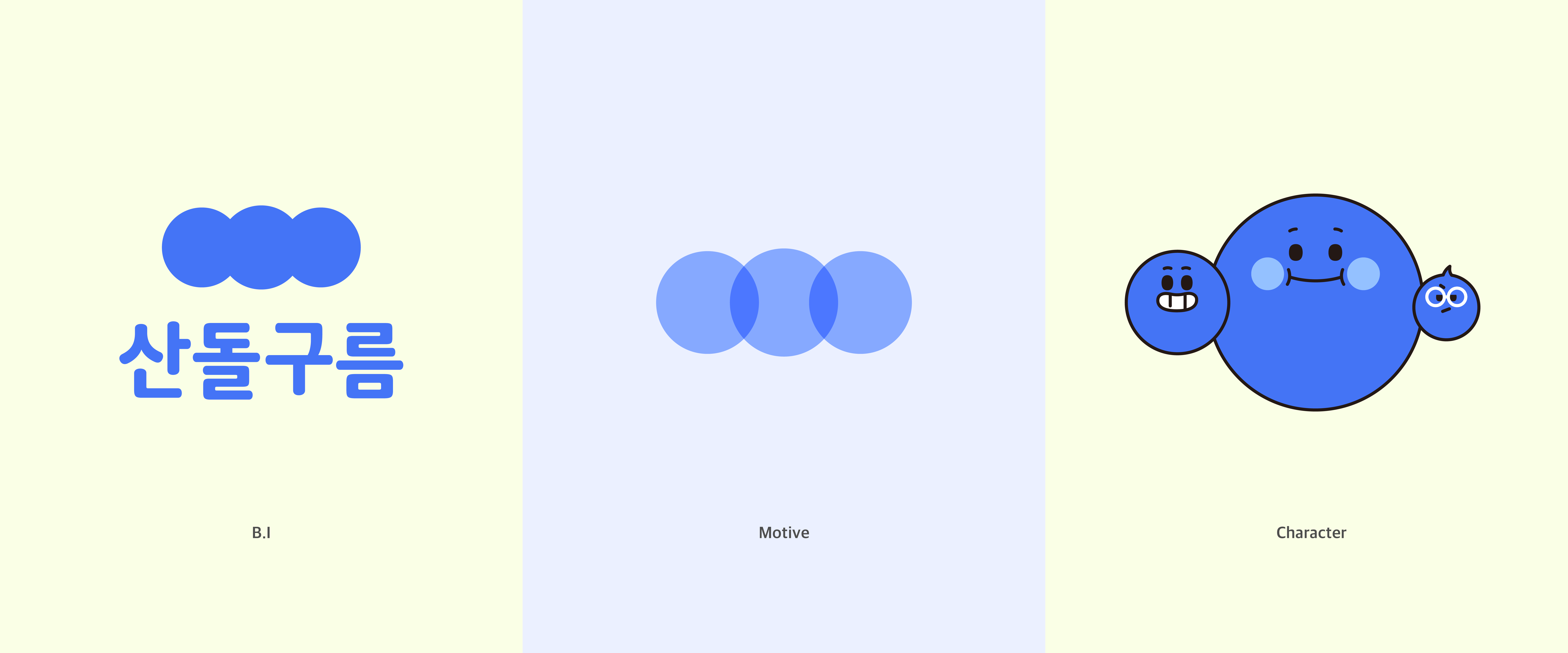
์บ๋ฆญํฐ ๋ชจํฐ๋ธ
ํฐํธ๋ฅผ ์๋ฉด ๋ณด์ด๋ ๋ํ
์ผ
์ด์ ์ฐ๋๊ตฌ๋ฆ ํจ๋ฐ๋ฆฌ์ ๊ตฌ์ฑ์์ ์๊ฐํ ์ฐจ๋ก์ธ๋ฐ์. ํฐํธ์ ์ฌ๋ฌ ๊ฐ์ง ํน์ฑ ์ค์์๋ ๋น๊ต์ ์ฝ๊ฒ ์ ํ ์ ์๋ ๊ฐ๋
์ธ ์ธ๋ฆฌํ, ๋ณผ๋, ์ดํค๋ฆญ 3๊ฐ์ง ํฐํธ ์คํ์ผ์ ์์ธํํด <์ฐ๋๊ตฌ๋ฆ ํจ๋ฐ๋ฆฌ>๋ฅผ ๊ตฌ์ฑํ์ต๋๋ค.
์ธ๋ฆฌ๋ ์ธ๋ฆฌํ์ ํน์ง์ ๋ฐ์ํด ์ ์๋ ์บ๋ฆญํฐ์ธ๋ฐ์. ์ธ๋ฆฌํ๋ ๊ธ์์ ์ธ๋กํ ๋๋ ๊ฐ๋กํ์ ์์์ ๊ณผ ๋์ ์์ ๋ณผ ์ ์๋ ๋๊ธฐ์
๋๋ค. ์ด๋ฌํ ์ธ๋ฆฌํ์ ํน์ง์ ์ธ๋ฆฌ์ ํฐ ๋ฐ๊ณผ ๋ชจ์๋ก ํํํ์ต๋๋ค.
์ธ๋ฆฌ SERI
๋ณผ๋๋ ๋ณผ๋์ ํน์ง์ ์ ์ฉํ ์บ๋ฆญํฐ์
๋๋ค. ์ฒ ๋ด๋ ์์๊ฒ ์ง๋ง ๋ค๋ฅธ ์บ๋ฆญํฐ์ ๋นํด์ ๊ฐ์ฅ ์ปค๋ค๋ ์บ๋ฆญํฐ์ธ๋ฐ์. ์ ์ดํด๋ณด๋ฉด ๋ณผ๋ ํฐํธ๊ฐ ์ฃผ๋ ๋ฌด๊ฒ๊ฐ๊ณผ ๊ท๋ชจ๊ฐ์ ํน์ฑ ์ธ์๋ ์ธ์๋ ์ ๊ณต๊ฐ์ด ์ข๋ค๋ ํน์ง์ ์บ๋ฆญํฐ์ ํ๋ค๋ฆฌ ํํ์ ํตํด์ ๋ฐ์ํด ๋ดค์ด์. ํ๋ค๋ฆฌ๊ฐ ๋๊ป๊ฒ ํํ๋์ด ์งง์ ๋ณด์ด๊ธฐ๋ ํ๋๋ฐ์. ๊ทธ๋์ ์ ๋ํ ๊ท์ฌ์ ๋ณด์ด๊ธฐ๋ ํฉ๋๋ค.
๋ณผ๋ BOLDY
ํ๋ฆฌ๋ ์ดํค๋ฆญ์ ํน์ง์ ๋ฐ์ํ ์บ๋ฆญํฐ์
๋๋ค. ์ดํค๋ฆญ์ ํ๋์์ ๊ฐ์กฐ์ ์๋ฏธ๋ก ์ฌ์ฉํ๋ ์ผ์ด ๋ง์๋ฐ์. ์ดํค๋ฆญ ํฐํธ์ ์ญ์ฌ๋ฅผ ๋ฐ๋ผ๊ฐ ๋ณด๋ฉด ๊ฐ์กฐ์ ๋ชฉ์ ์ด์ธ์๋ ์ดํค๋ฆญ์ ๊ธฐ์ธ์ด์ง ํน์ฑ์ ํ์ฉํ์ฌ ์ง๋ฉด์ ๋ ๋ง์ ๋จ์ด๋ฅผ ์ธ์ํ๊ธฐ ์ํด ์ดํค๋ฆญ์ ์ฌ์ฉํ๋ค๊ณ ํด์. ์ฌ๋ฐ์ฃ ? ์ด๋ฌํ ์ด์ผ๊ธฐ๋ฅผ ๊ทผ๊ฑฐ๋ก ํ๋ฆฌ์ ํฌ๊ธฐ๋ฅผ ๊ฐ์ฅ ์๊ณ ์๋ชจ์ต์ด ๊ธฐ์ธ์ด์ง ํํ๋ก ๋ํ๋์ต๋๋ค. ๊ทธ๋ฆฌ๊ณ ์ดํค๋ฆญ์ ๊ธฐ์ธ์ด์ง ํน์ง์ ์บ๋ฆญํฐ์ ์ฑ๊ฒฉ์๋ ํฌ์ฌํด ์๋ฑํ ์ฑ๊ฒฉ๊ณผ ํ๋๋ก ๋ด์๋ด๋ ค๊ณ ํ์ต๋๋ค.
ํ๋ฆฌ TALI
์กฐ๊ธ ๋ ๊ตฌ์ฒด์ ์ผ๋ก ์ด์ผ๊ธฐ๋ฅผ ํ์ด๋ณด์๋ฉด ๊ฐ์ฅ ๋จผ์ ์ค๋ช
ํ ์ธ๋ฆฌ๋ ๋ ๊ทค๋ฌ์ด๊ธฐ๋ ํฉ๋๋ค. ๋ ๊ทค๋ฌ๋ ํฐํธํจ๋ฐ๋ฆฌ ์ค์์ ๊ธฐ์ค์ด ๋๋ ๊ธฐ๋ณธํ ํฐํธ๋ผ๊ณ ์๊ฐํ์๋ฉด ๋๋๋ฐ์. ์ธ๋ฆฌ๊ฐ ๋ ๊ทค๋ฌ๋ก์ ‘์ฐ๋๊ตฌ๋ฆ ํจ๋ฐ๋ฆฌ’ ๊ธฐ์ค์ ์ก์์ฃผ๋ ์ญํ ์ ํ๊ณ ์์ต๋๋ค. ๋๋ถ์ ๋ณผ๋์ ๋ถํผ๊ฐ์ ๊ฐ์กฐํ ์ ์๊ณ , ํ๋ฆฌ์ ๊ธฐ์ธ๊ธฐ์ ์์ ํฌ๊ธฐ๋ฅผ ์ฝ๊ฒ ์ฒด๊ฐํ ์ ์์ด์.
‘์ฐ๋๊ตฌ๋ฆ ํจ๋ฐ๋ฆฌ’๋ ์์ ์ด์ผ๊ธฐํ ๊ฒ์ฒ๋ผ, ๋ค์ ๋ฏ์ค ์ ์๋ ํฐํธ์ ์ด์ผ๊ธฐ๋ฅผ ์น๊ทผํ๊ฒ ์ ๋ฌํ๊ณ ์ ํ๋ ๋ชฉ์ ์ผ๋ก ์ ์๋์์ต๋๋ค. ํ์ฌ ‘์ฐ๋๊ตฌ๋ฆ ํจ๋ฐ๋ฆฌ’๋ ์ฐ๋๊ตฌ๋ฆ ์ธ์คํ๊ทธ๋จ์์ ๋ง๋๋ณผ ์ ์๋๋ฐ์. ์ฌ๋ฌ๋ถ์ ๊ด์ฌ์ด ๋ง์์ง๋ค๋ฉด ๊ทธ ์ธ์ ๊ณต๊ฐ์ผ๋ก ํ์ฅ๋์ด ๋์ฌ์ง๋ ๋ชฐ๋ผ์. ๋๊ตฌ๋๊ตฌ. ๋ค์์ ๋ ๋ง๋์.